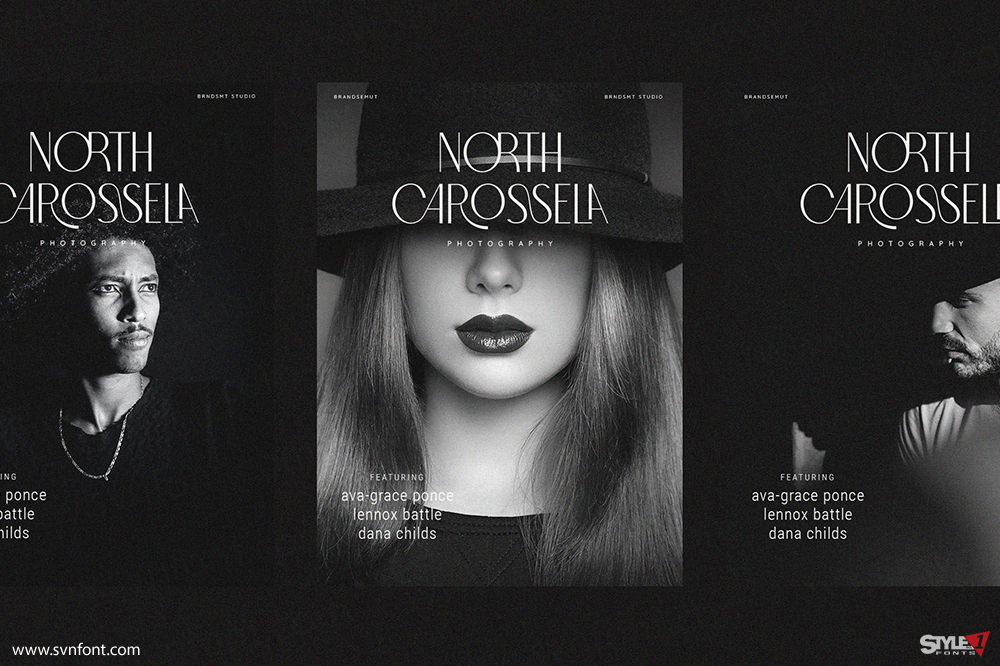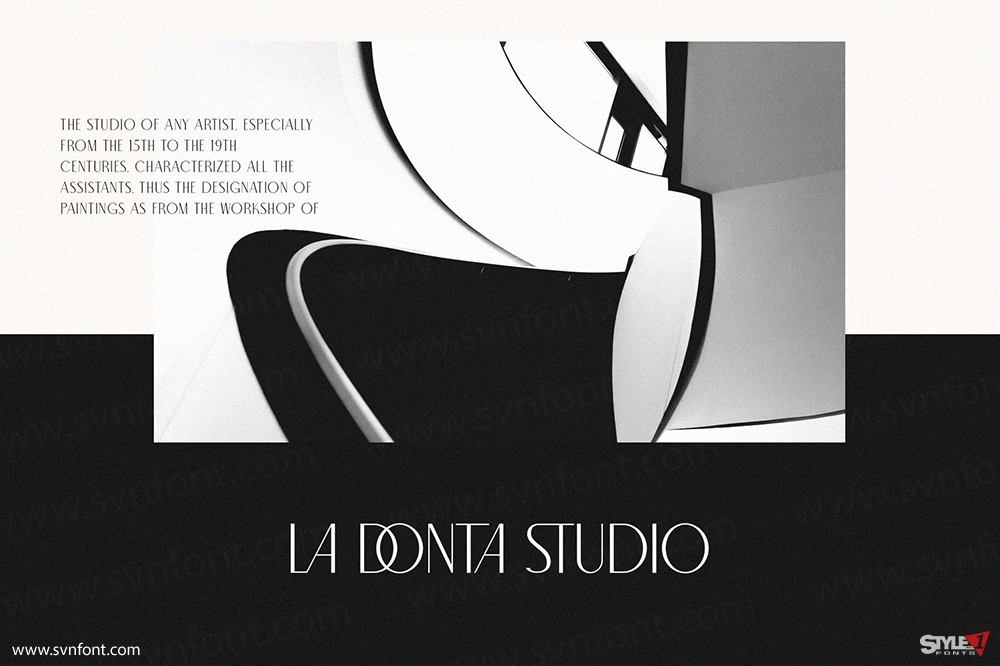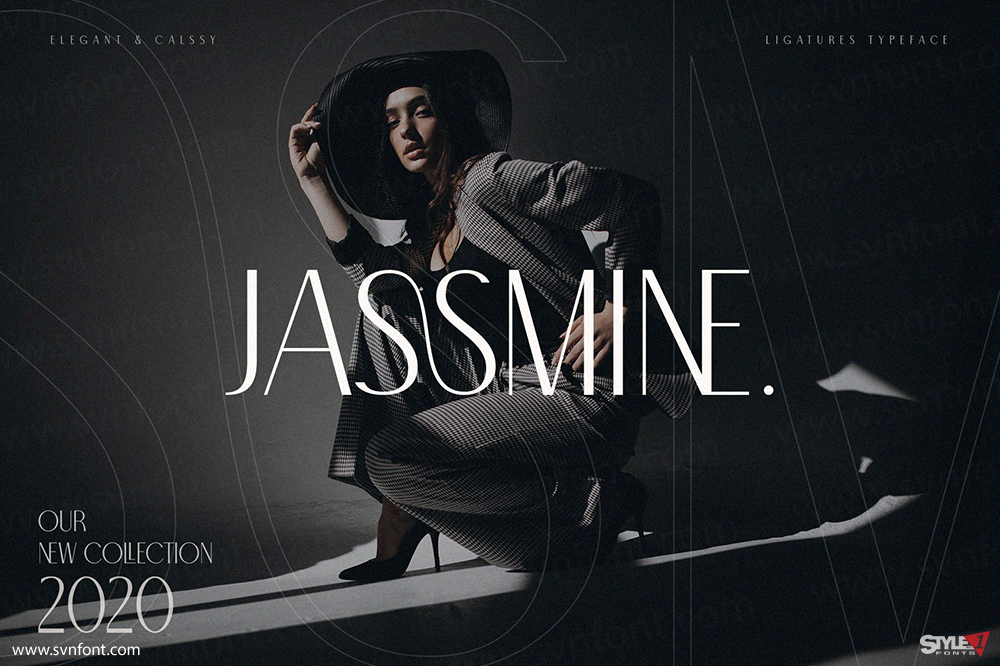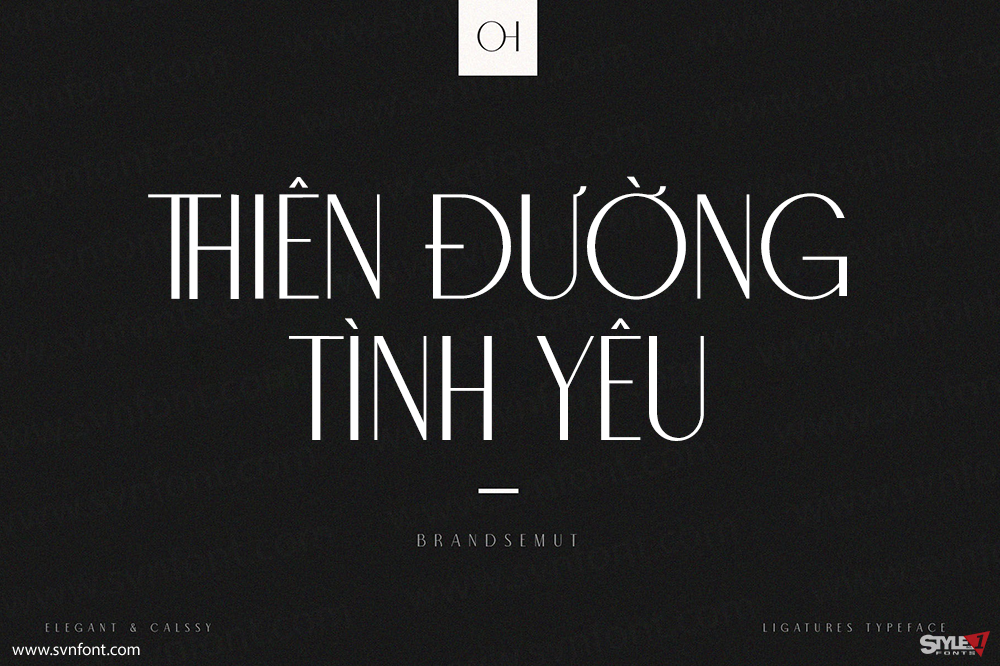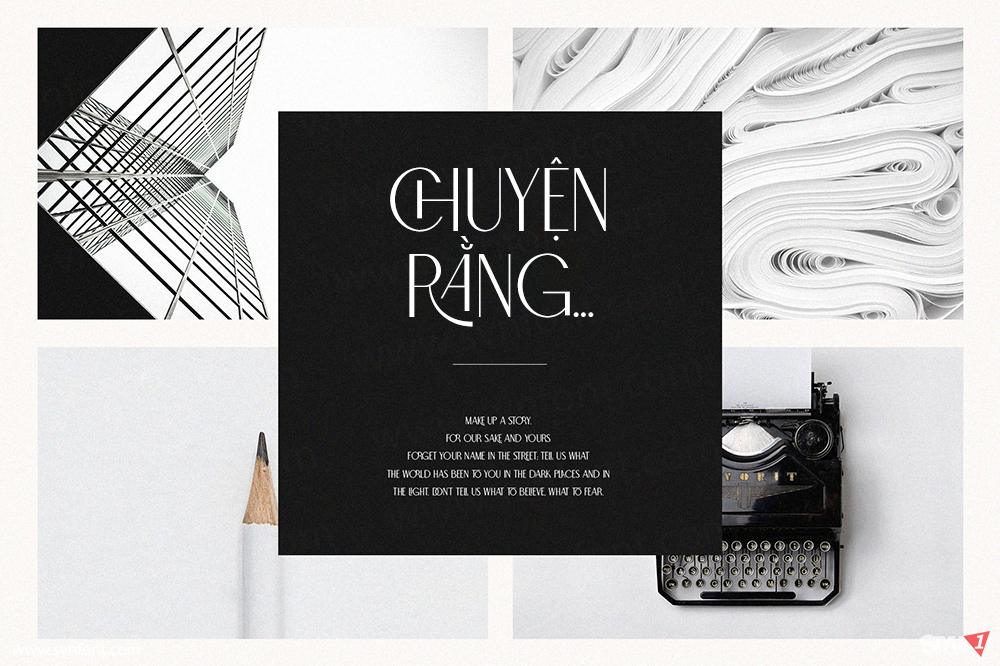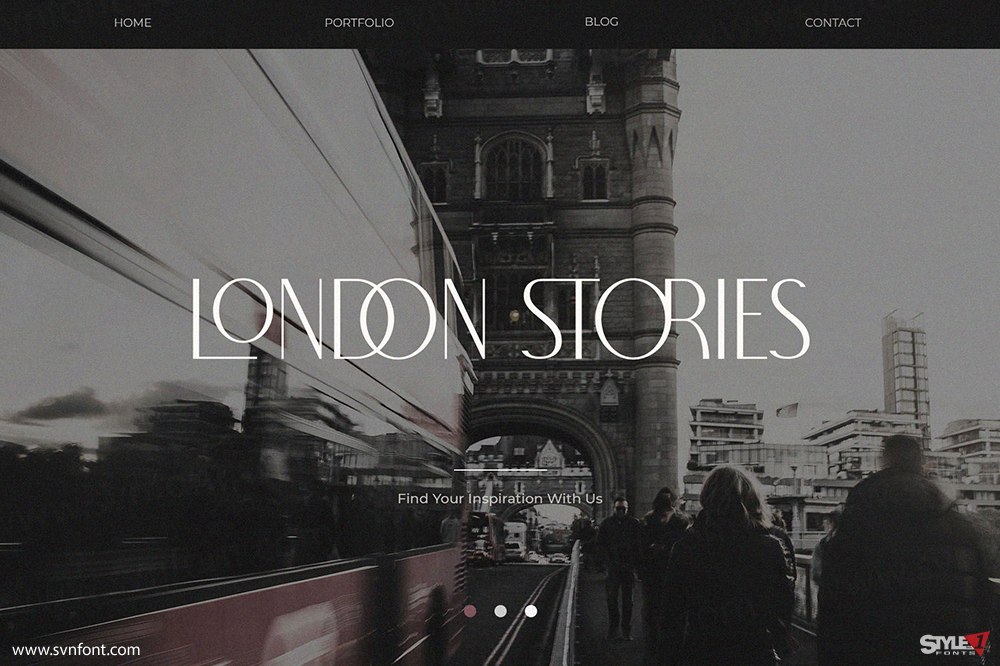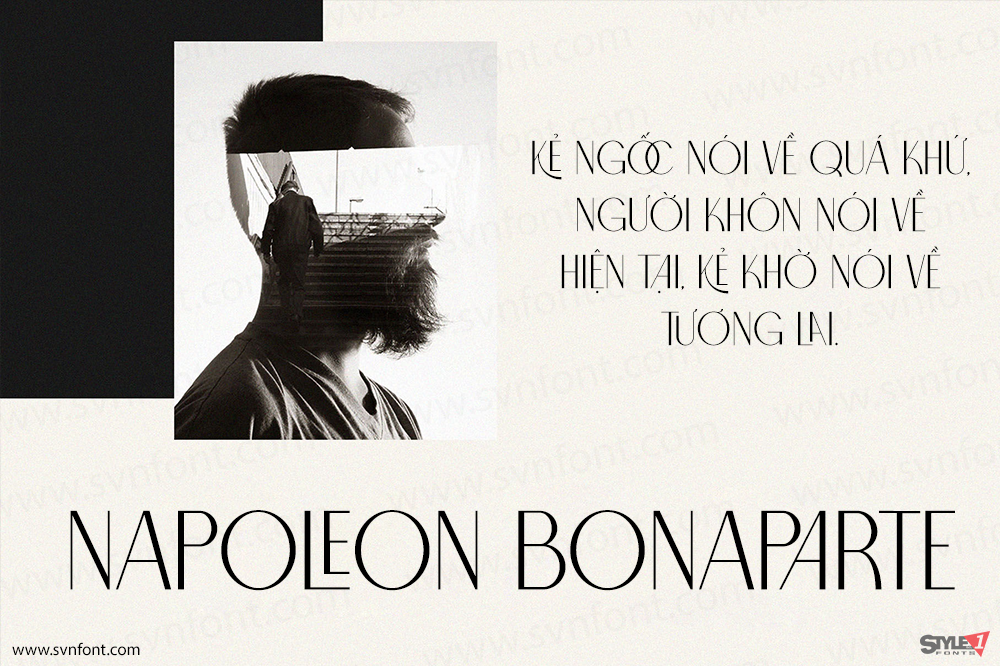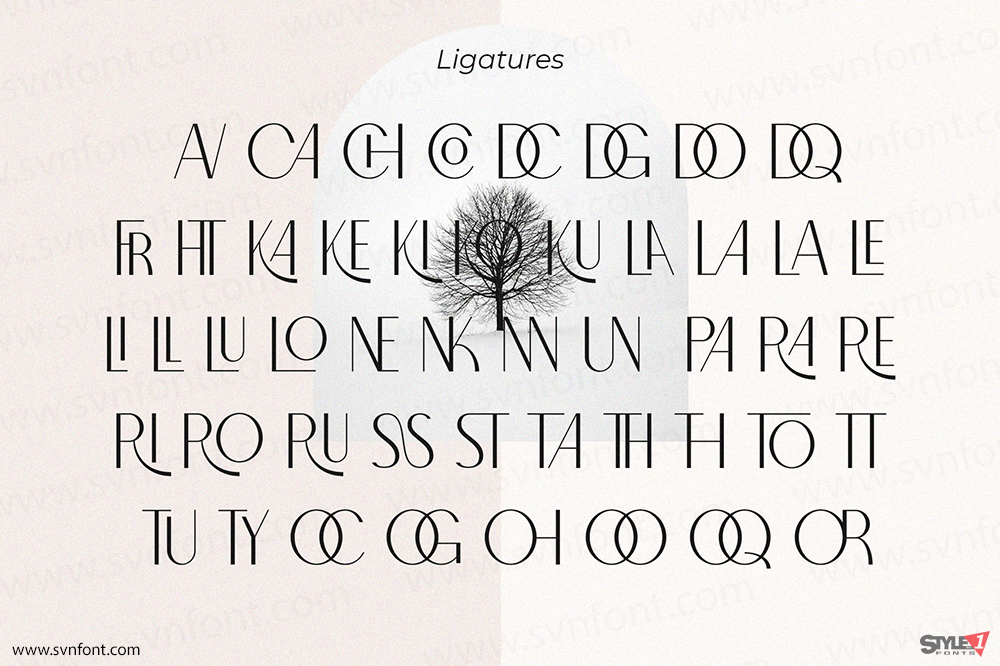
Giới thiệu North Carossela mới, một font Ligature Sans!!! North Carossela là một kiểu chữ sans thanh lịch và đẳng cấp – đã được kết hợp sẵn sàng để sử dụng cùng nhau cho thiết kế tiếp theo của bạn! Đối với những ai đang cần một chút thanh lịch, phong cách, đẳng cấp, sang trọng và hiện đại cho các thiết kế của mình, font chữ này được tạo ra dành cho bạn!
North Carossela được xây dựng với các tính năng OpenType và bao gồm các nét nối (ligatures), ký tự thay thế (alternates), số, dấu câu, và nó cũng hỗ trợ các ngôn ngữ khác.
Nhà thiết kế: Ahmad Sidiq
Nhà phát hành: Brandsemut